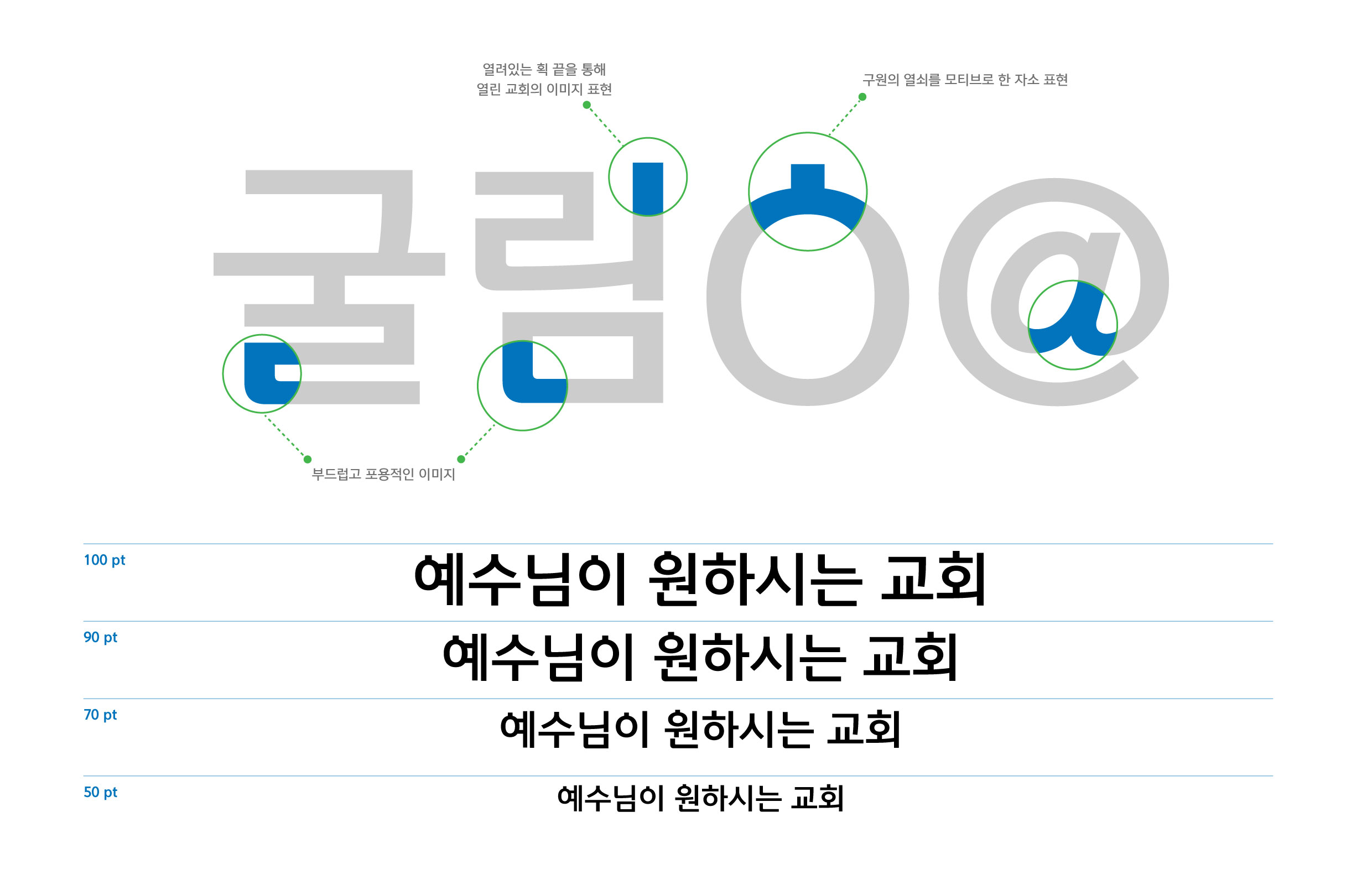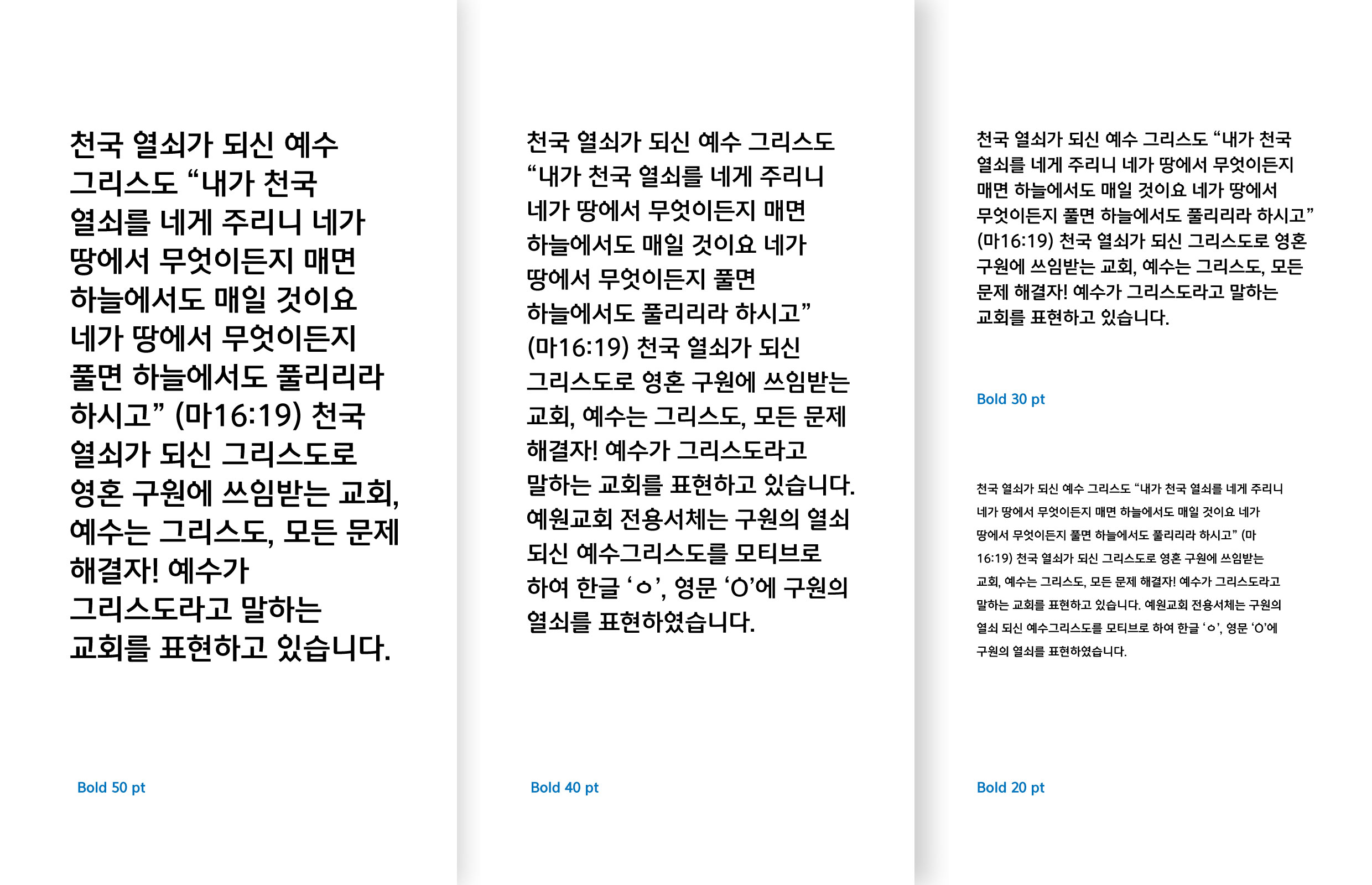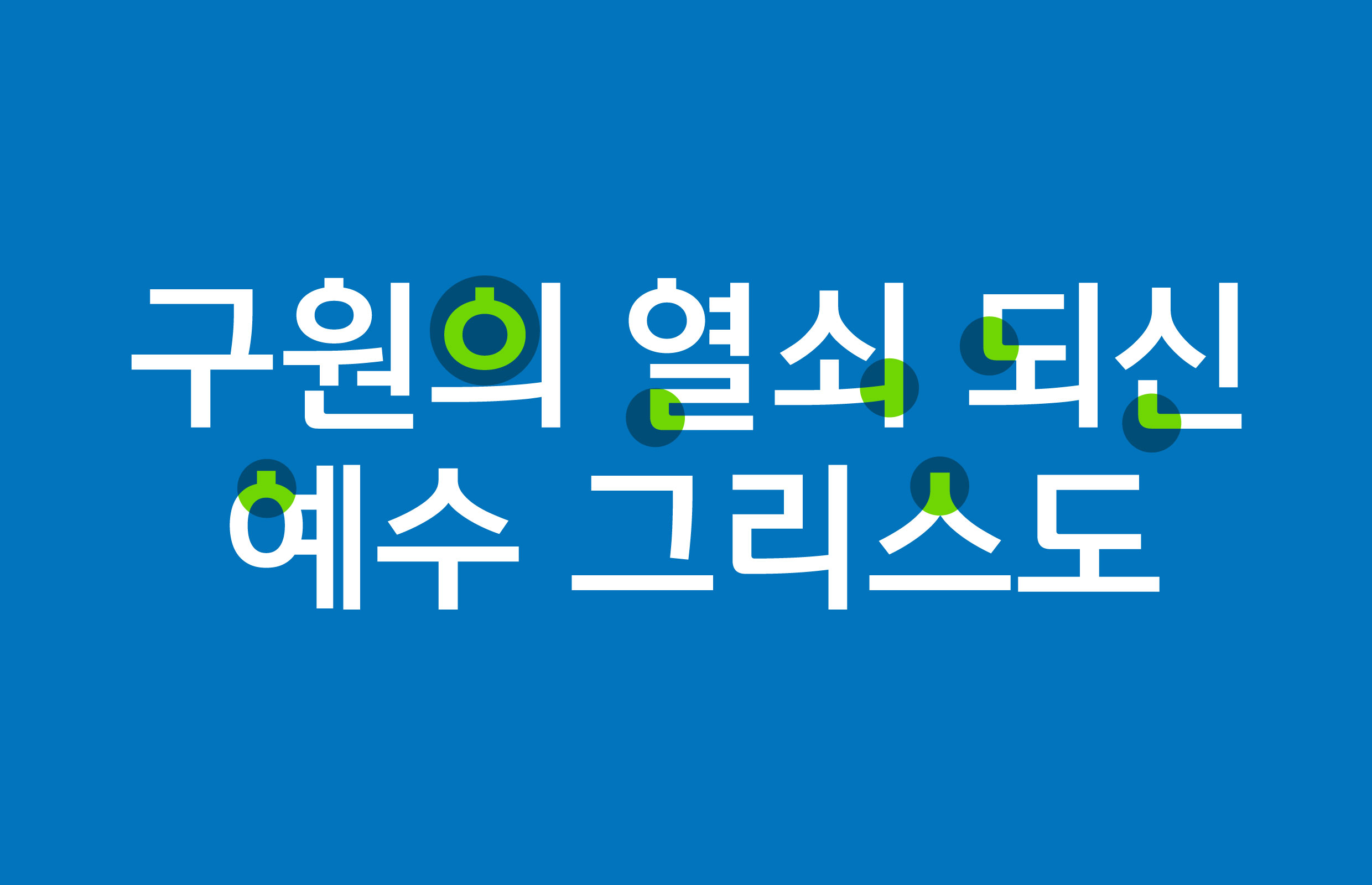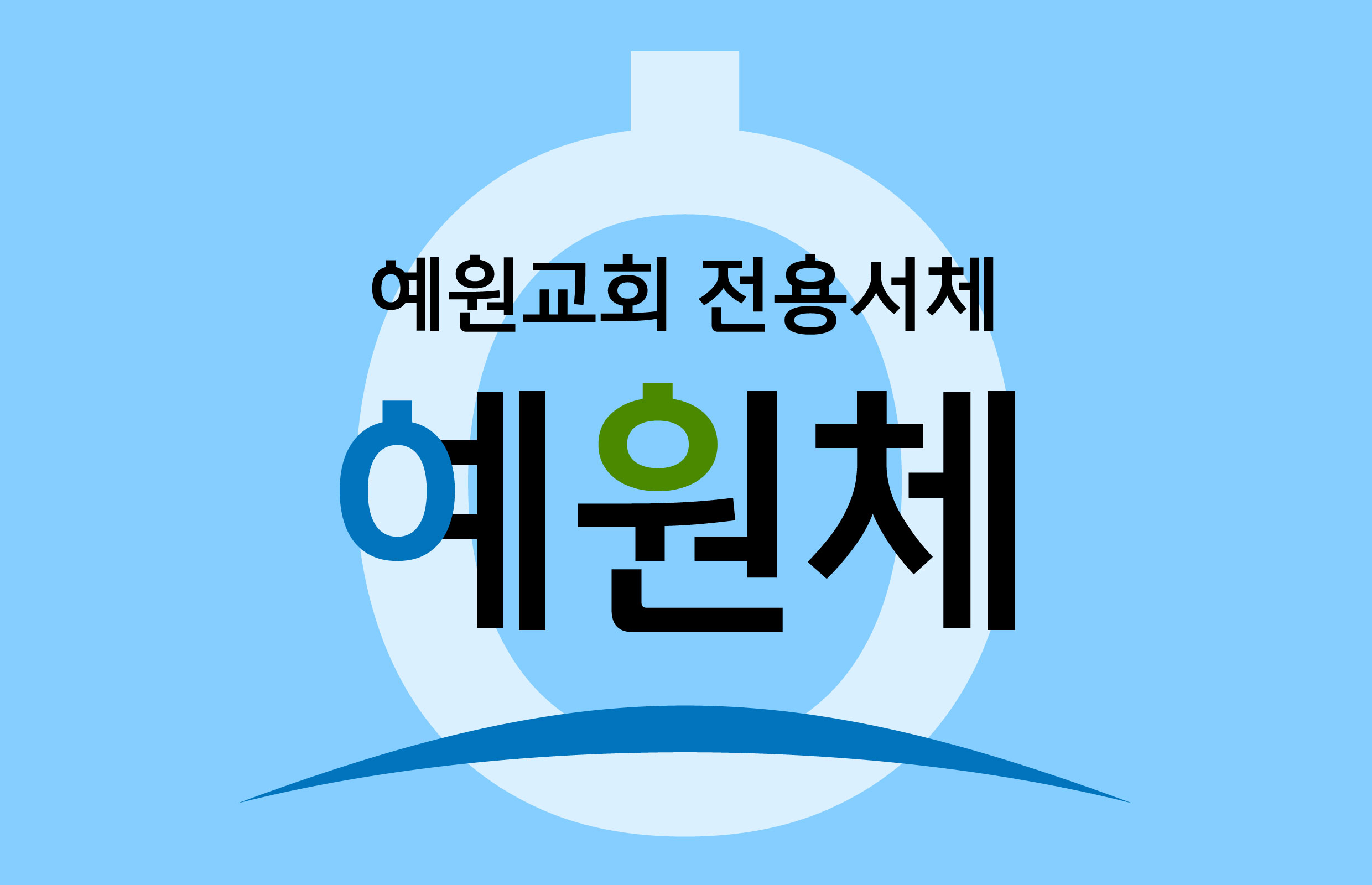
예원교회
예원교회 [예원체]
서울시 등촌동 소재의 예원교회 전용서체. “내가 천국 열쇠를 네게 주리니 네가 땅에서 무엇이든지 매면 하늘에서도 매일 것이요 네가 땅에서 무엇이든지 풀면 하늘에서도 풀리리라 하시고”(마태복음 16장 19절) 구절을 모티브로, ‘o’꼴에 열쇠구멍을 표현하여 아이덴티티를 담았다.